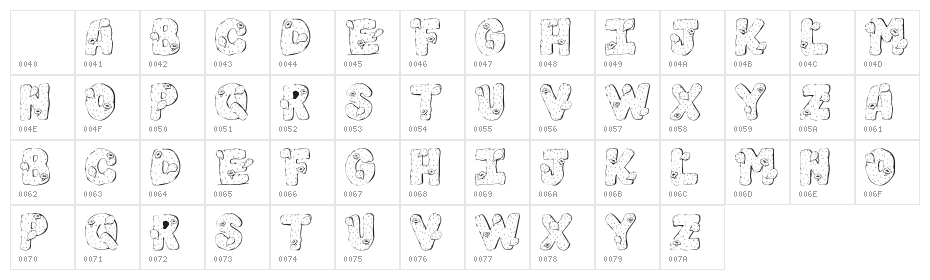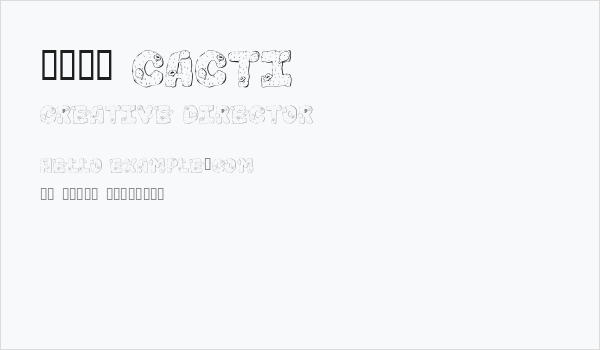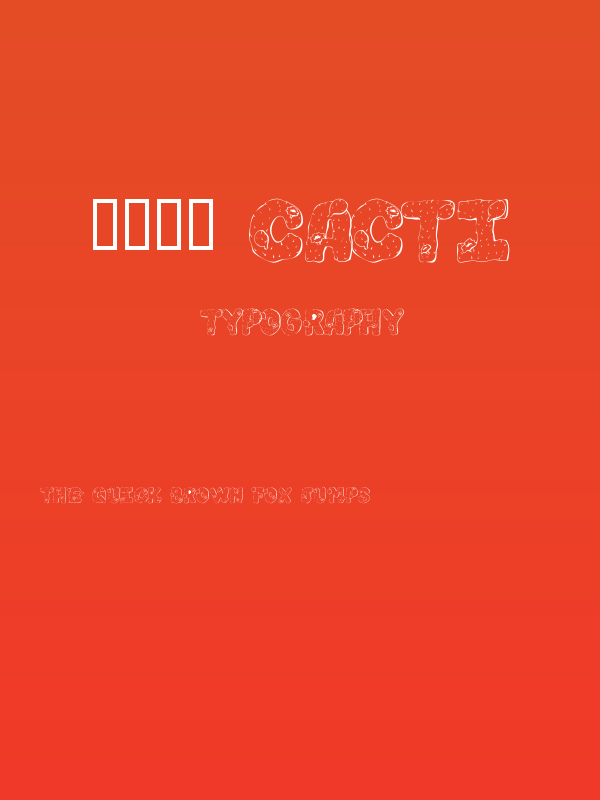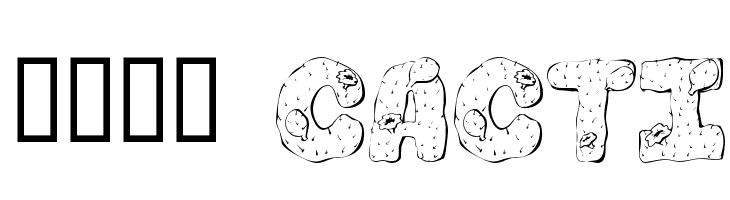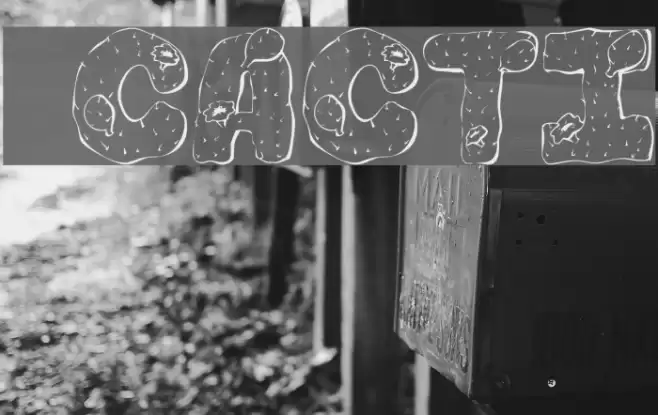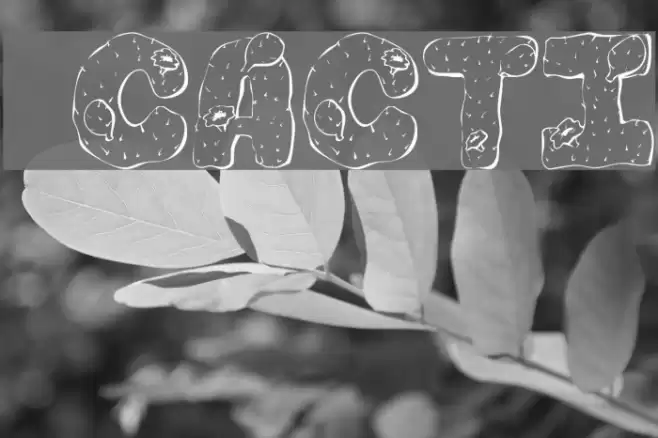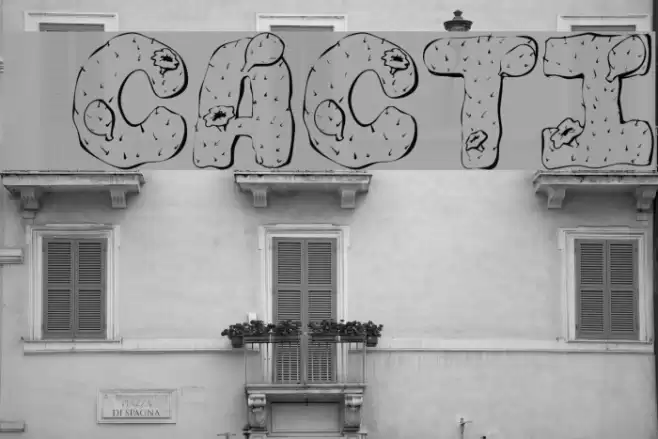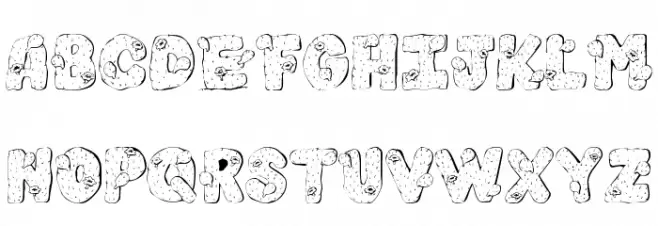
101! Cacti Font
✎ Decorative
| Proyectos propuestos | Ideal for children's books, party invitations, posters, and branding for playful or nature-themed products. |